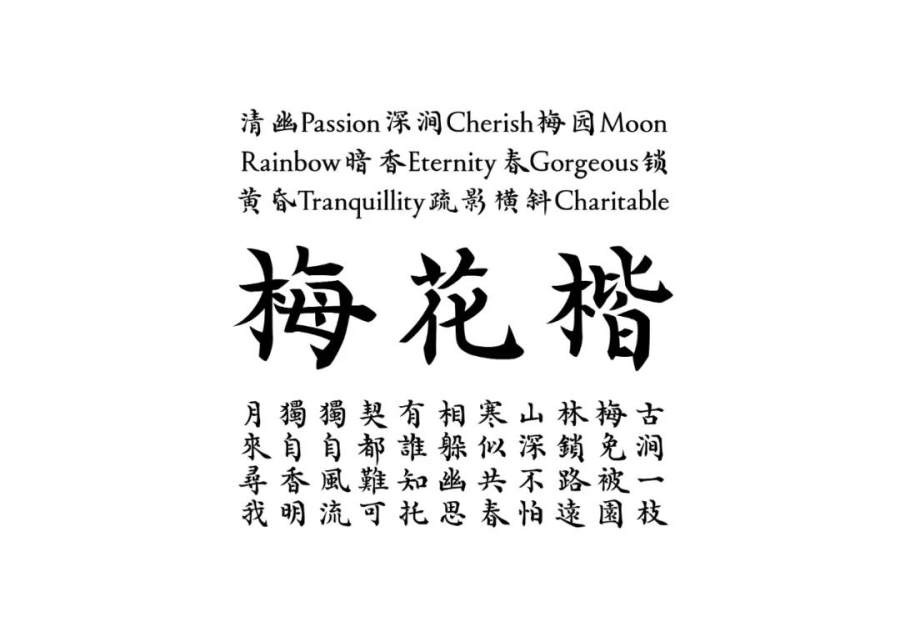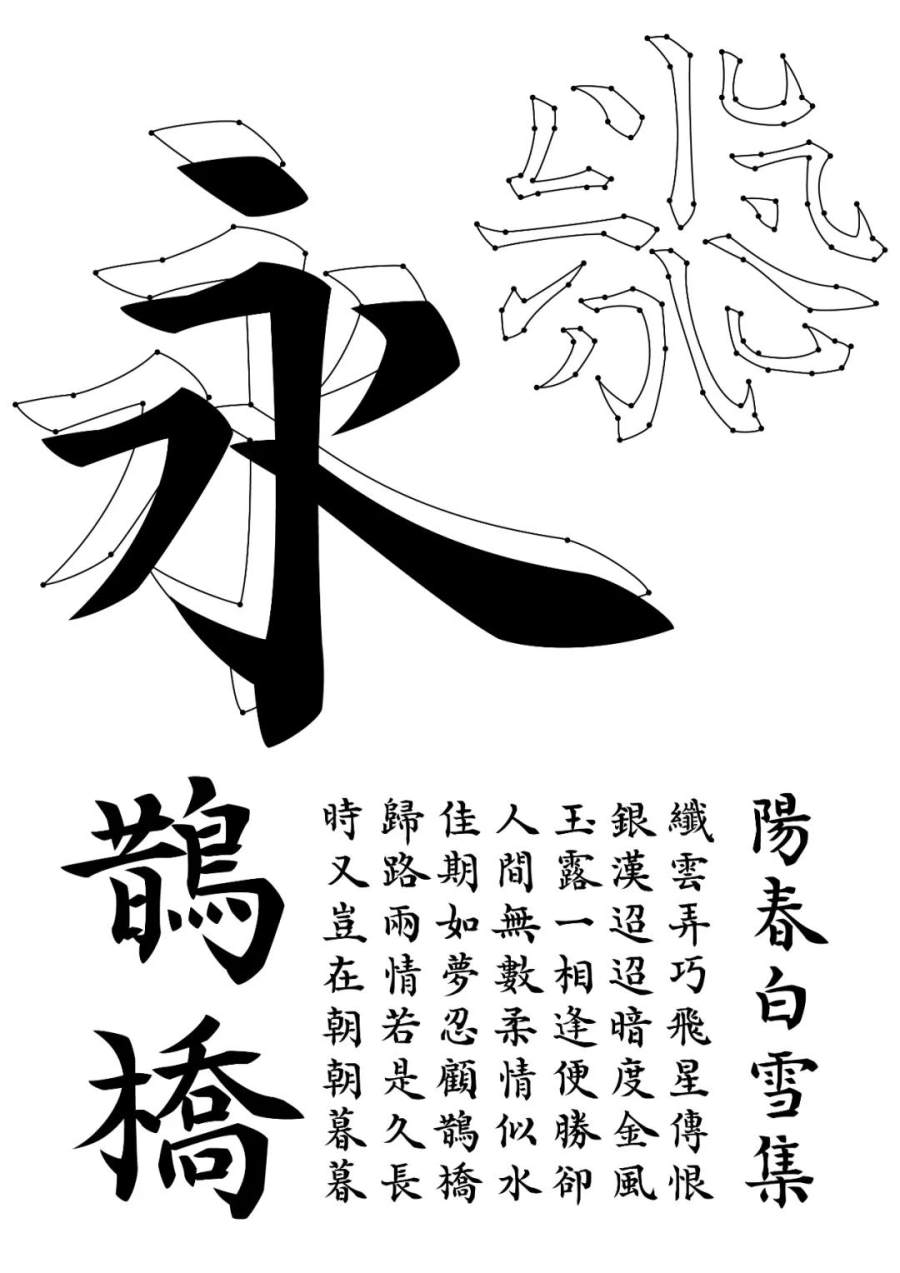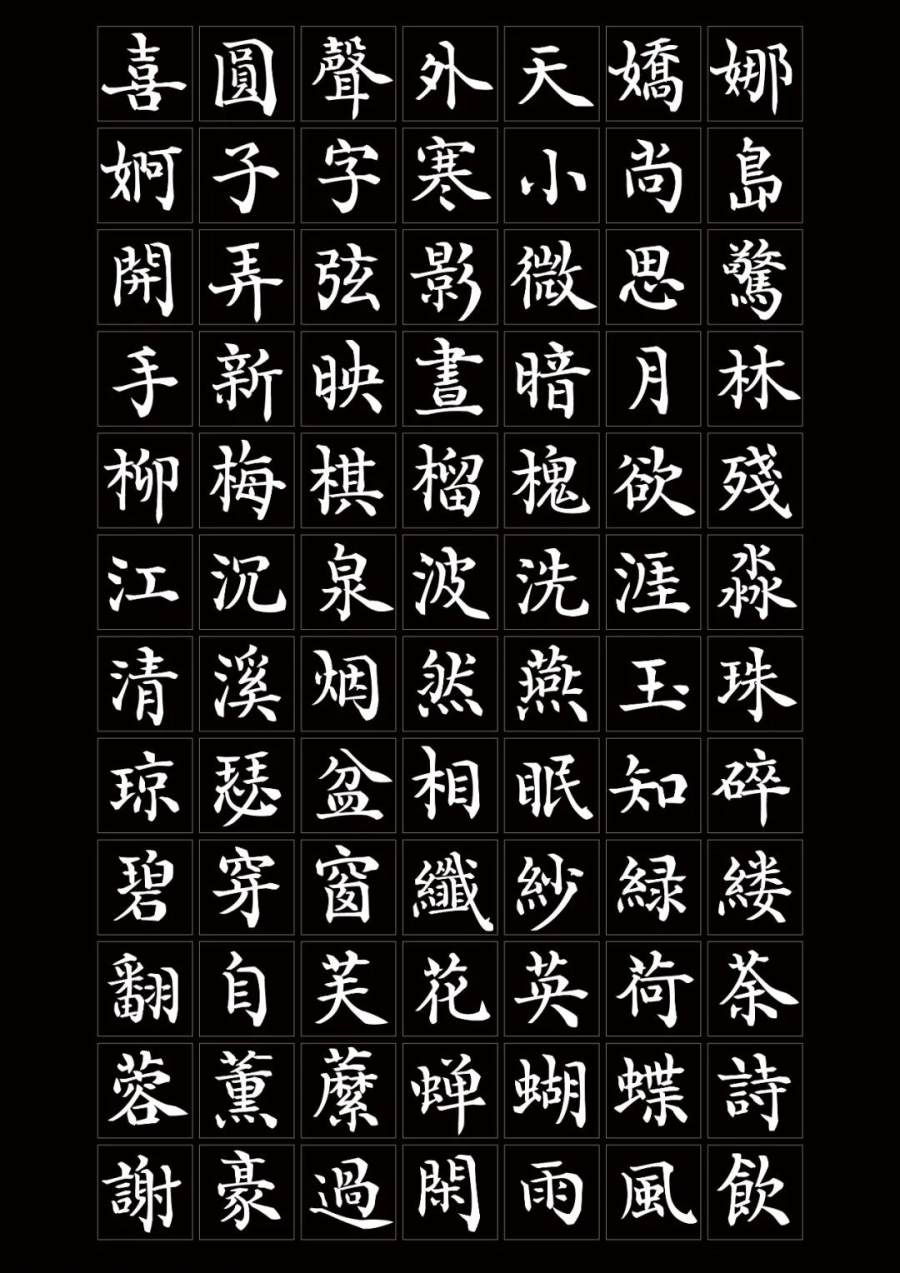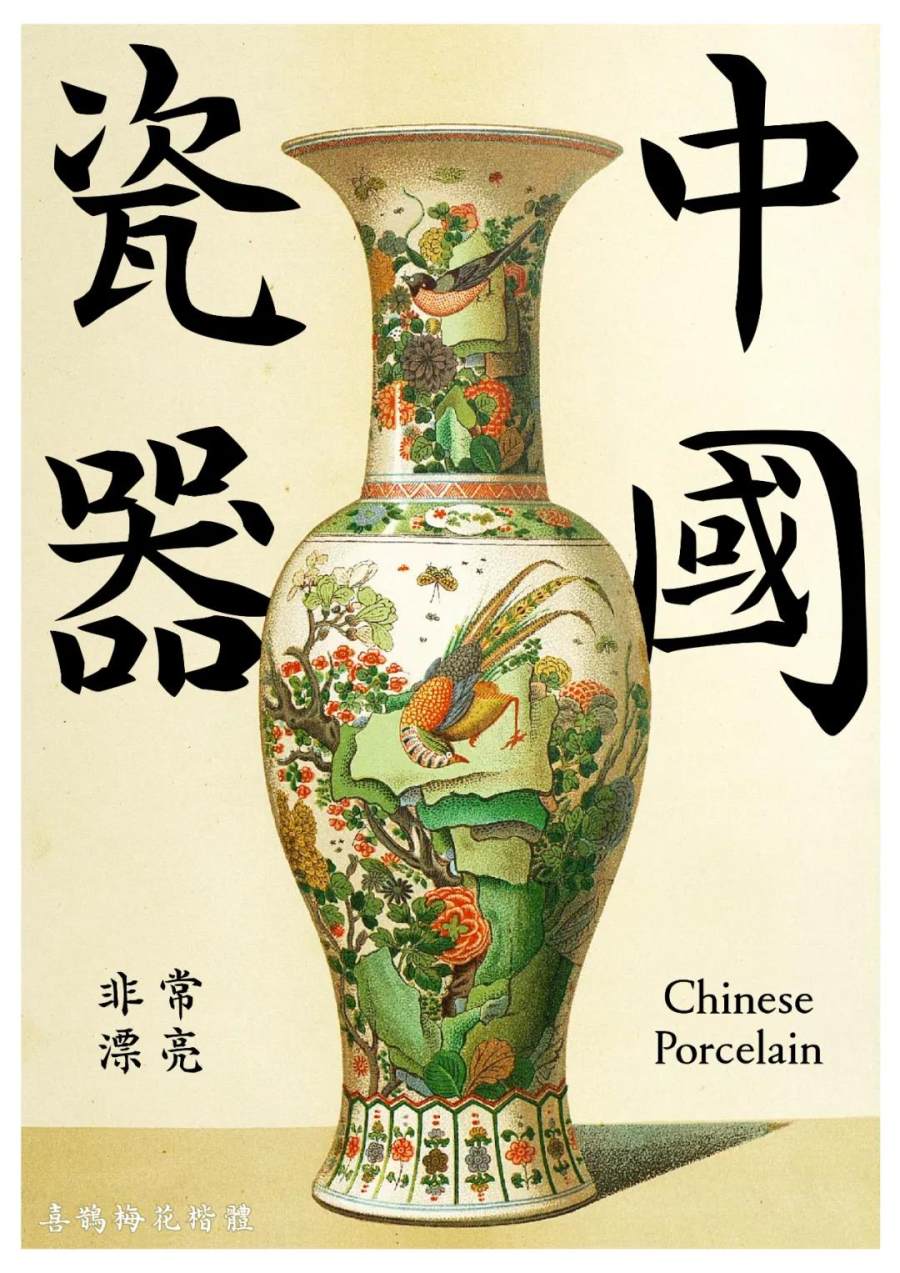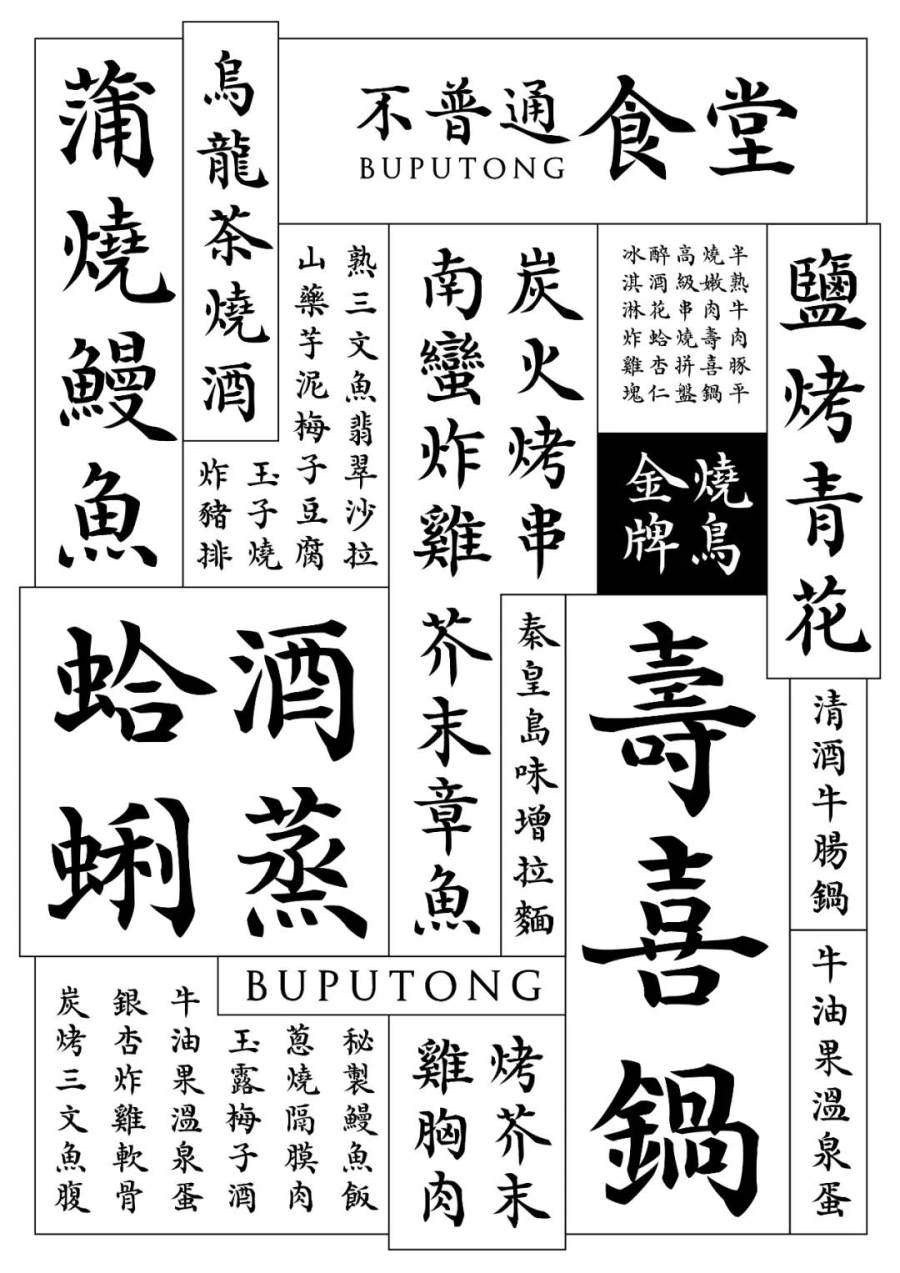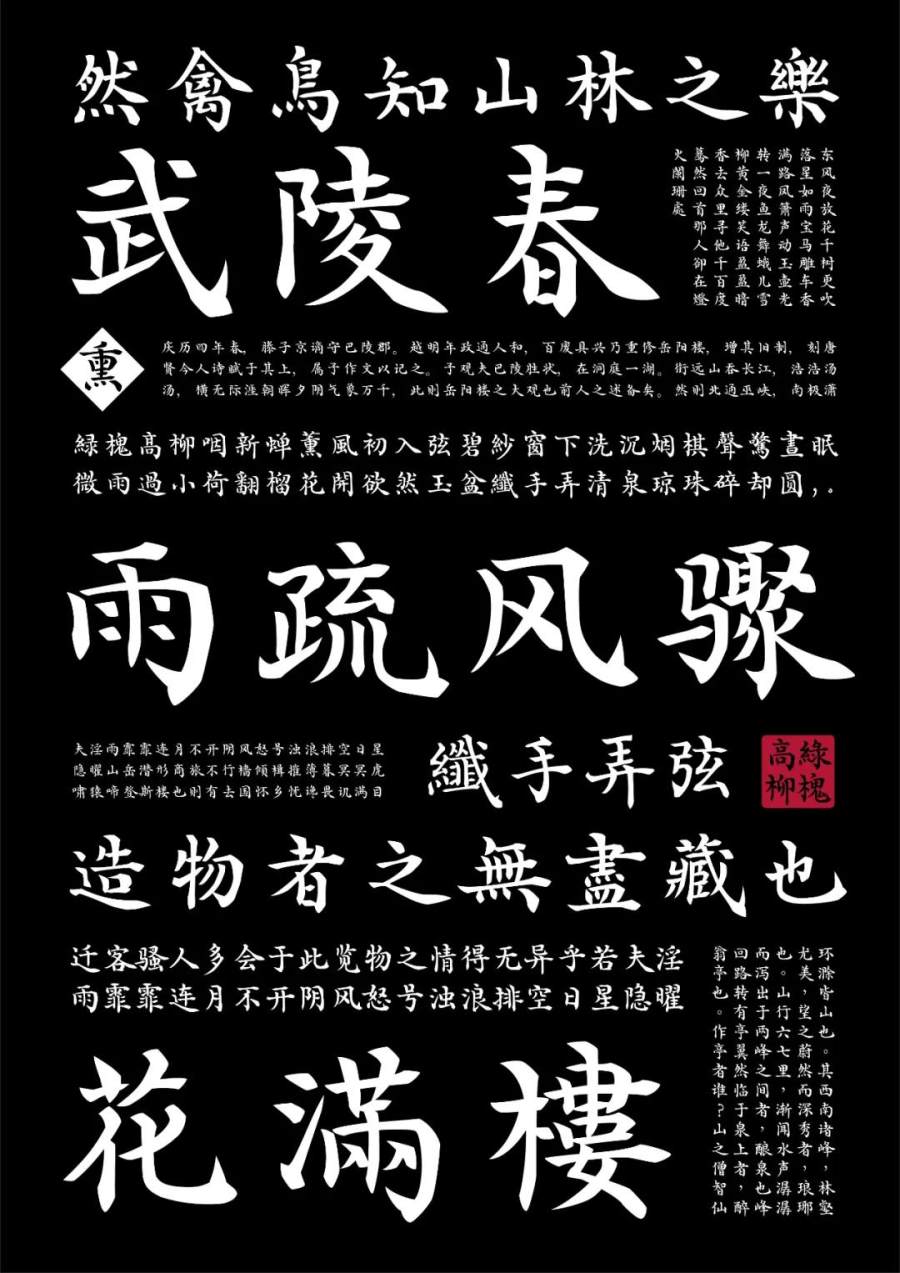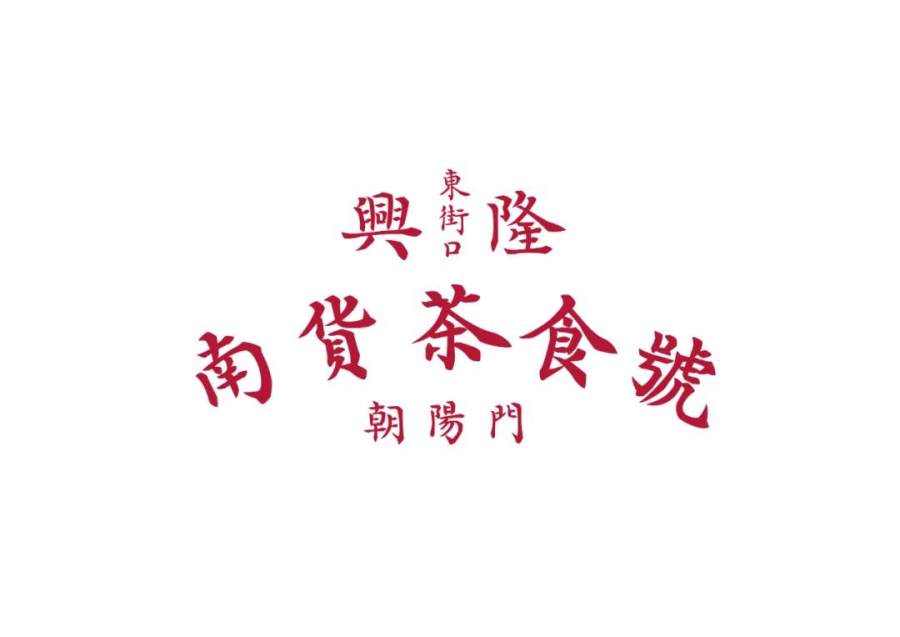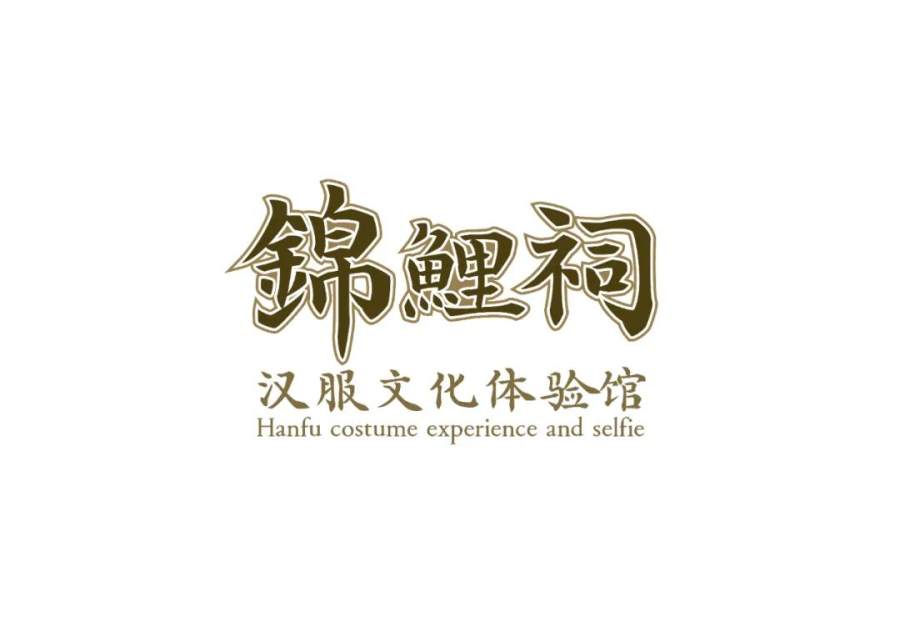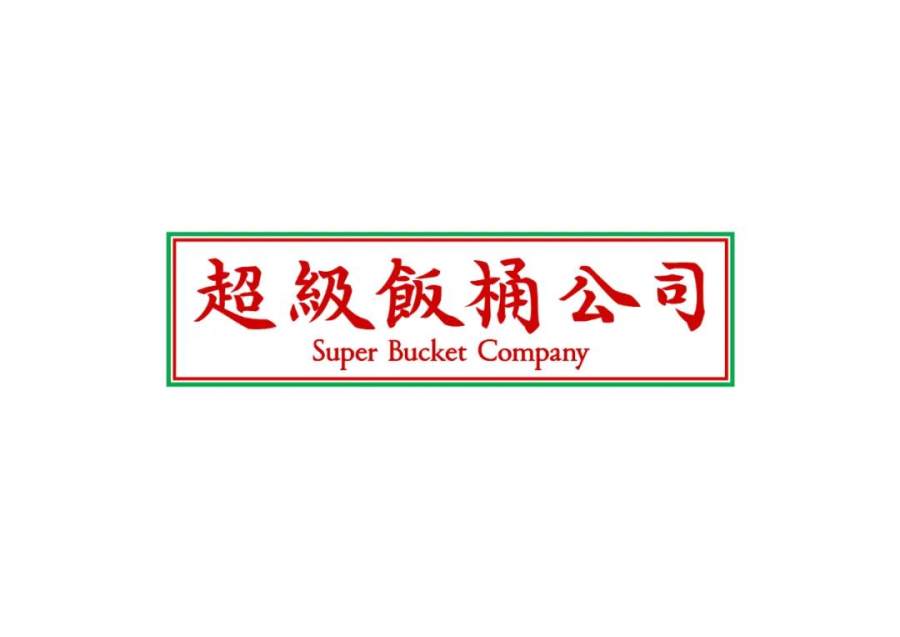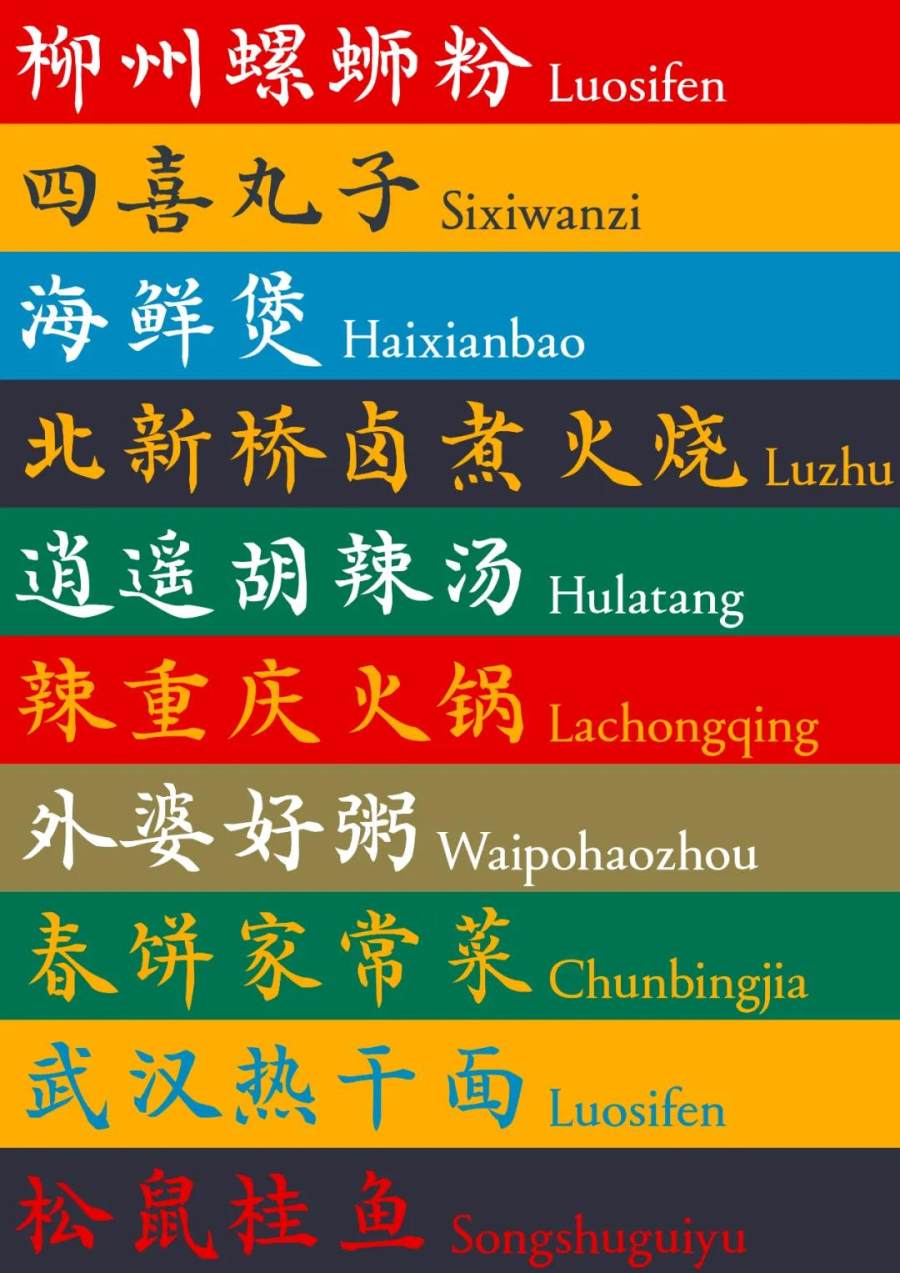
字体设计这事,
竟然越做越觉得难,也越加有意思,就是在字体里面,你总能有新发现、新感受和伴随而来的新沮丧、新痛苦。
一套常用的简繁字库有着大于10000的字符量。对造字者而言,像是要撒上万粒种子,种出上万棵树苗,为了使之成林,还需要再浇灌、修剪数万次使其自洽规整。是漫长的过程。从全部做完时的自信,到回过头来发现新问题、然觉得自己仍然很菜鸡的沮丧,再到思考怎么变得更好的痛苦。相信是我们必须要经历的。
喜鹊梅花楷
来自大霖的字稿!
此字体获得【GDC设计奖2019 优异奖】殊荣!
先来各方位展示一下梅花楷:
字体介绍:此字参考清代古籍钞本创作而成,在古籍字的基础上进行归纳与几何化抽象处理,创作成符合现代审美的书法矢量字形。整套字体柔媚娟秀,笔形清劲峻峭,是平衡刚与柔的楷体尝试。
适用于:中国味道及复古的标志标题等文字需求,如中式品牌、传统餐饮、复古流行、奶茶食品、国风影视字幕等。
很多时候,我们为啥字体做的慢呢,其实是在创作之初的考量和纠结较多。其实如果仅仅是把古代手抄本的字迹或名家手写的书法复印下来翻刻为字库,远比如此一般重新改刻、设计,来的要快的多。但是那样并没有对字进行思考和归纳总结,我们自身也没什么提高。我认为书法风格字体,不等同于照搬书法,是要有取舍,对态势、对细节 并不是一味复制,而是“强调大特点,抹去小冗余”。此为我心里的字体之设计。所以在这一点上,大霖此字稿的出发点,非常优秀。